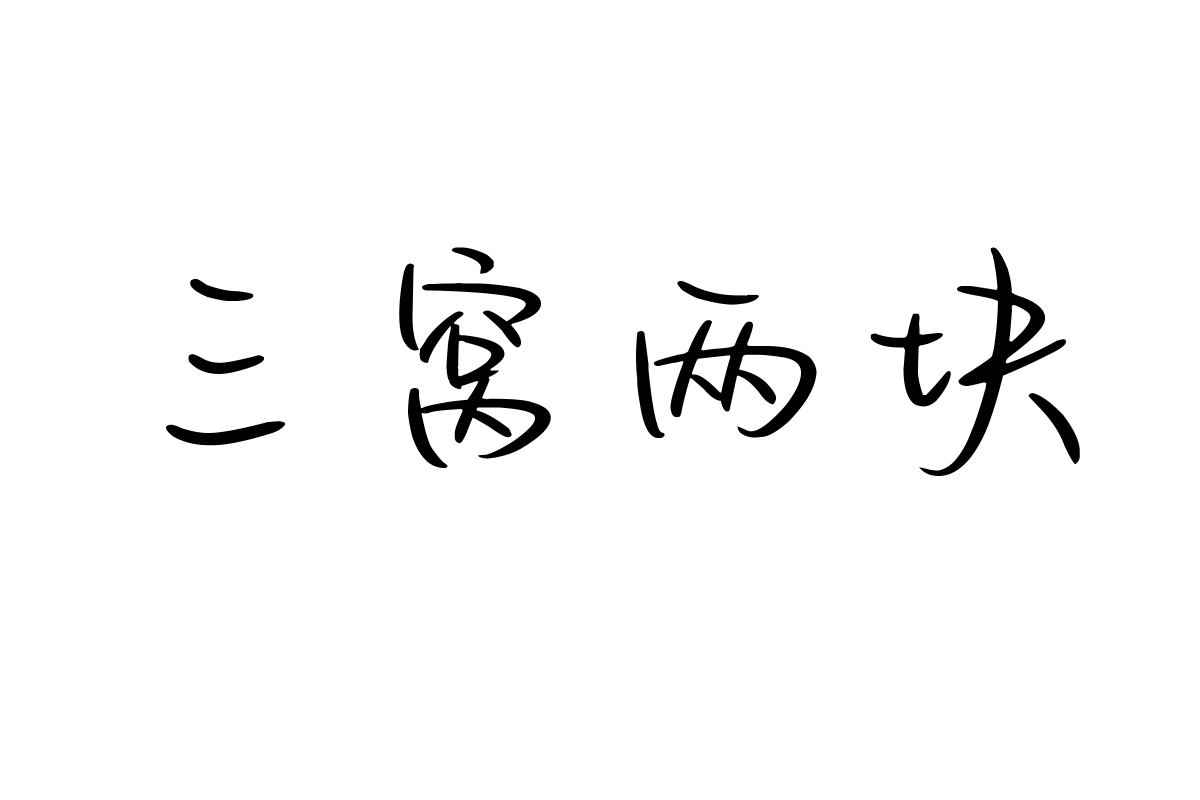
也字工厂猛犸手迹是一款具有独特书法风格的中文字体。这款字体采用了传统的手写笔触,将汉字笔画进行了重新设计,使其更加流畅自然。字体中的每一个笔画都仿佛在纸上流淌,给人一种古朴而优雅的感觉。
也字工厂猛犸手迹的字形结构紧凑,线条粗细适中,既有力量感又不失柔美。这种独特的设计风格使得这款字体在视觉上具有很强的冲击力,能够吸引人们的注意力。
此外,也字工厂猛犸手迹还注重细节的处理,每个字的间距、角度和位置都经过精心设计,使得整款字体看起来更加和谐统一。同时,这款字体还具有一定的可读性,即使在放大或缩小的情况下,也能够保证文字的清晰易读。
总的来说,也字工厂猛犸手迹是一款极具个性和艺术感的中文字体,适合用于需要强调个性和艺术氛围的设计项目中。